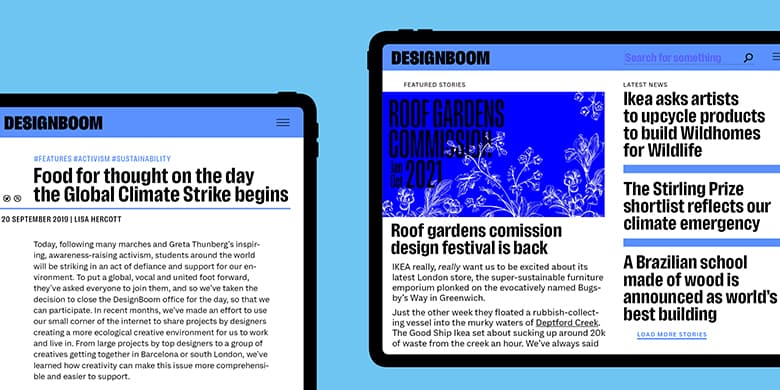
Lektorat
品牌:TypeTogether设计师:FlorianFecher发行时间:2020字库编码:Unicode分类:无衬线体字体属性:
Lektorat的27种风格在理性上有条不紊,在功能上无懈可击,体现文本编辑的多样性表达。
Methodical in rationale and irrepressible in function, Lektorat’s 27 styles are the embodiment of editorial expression.